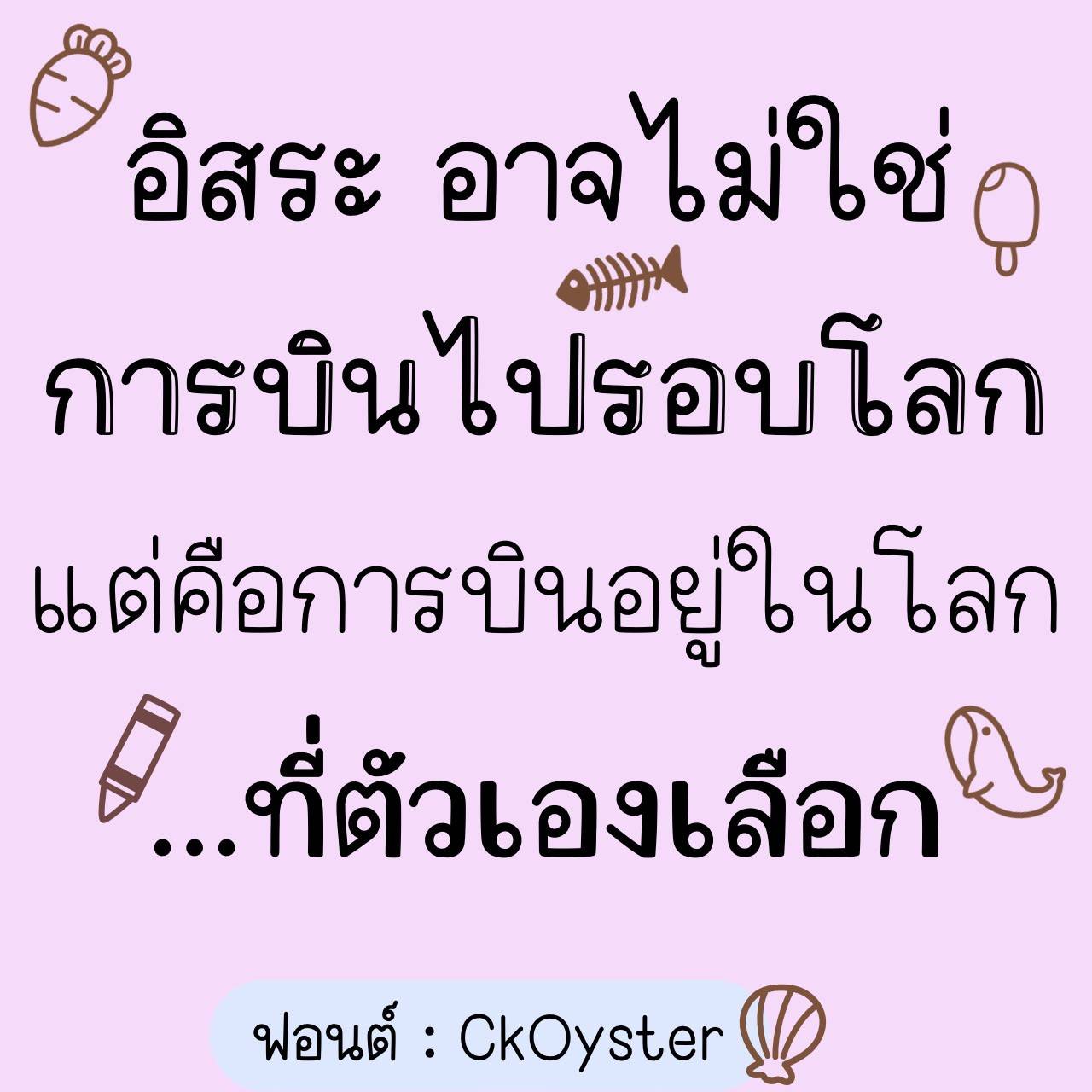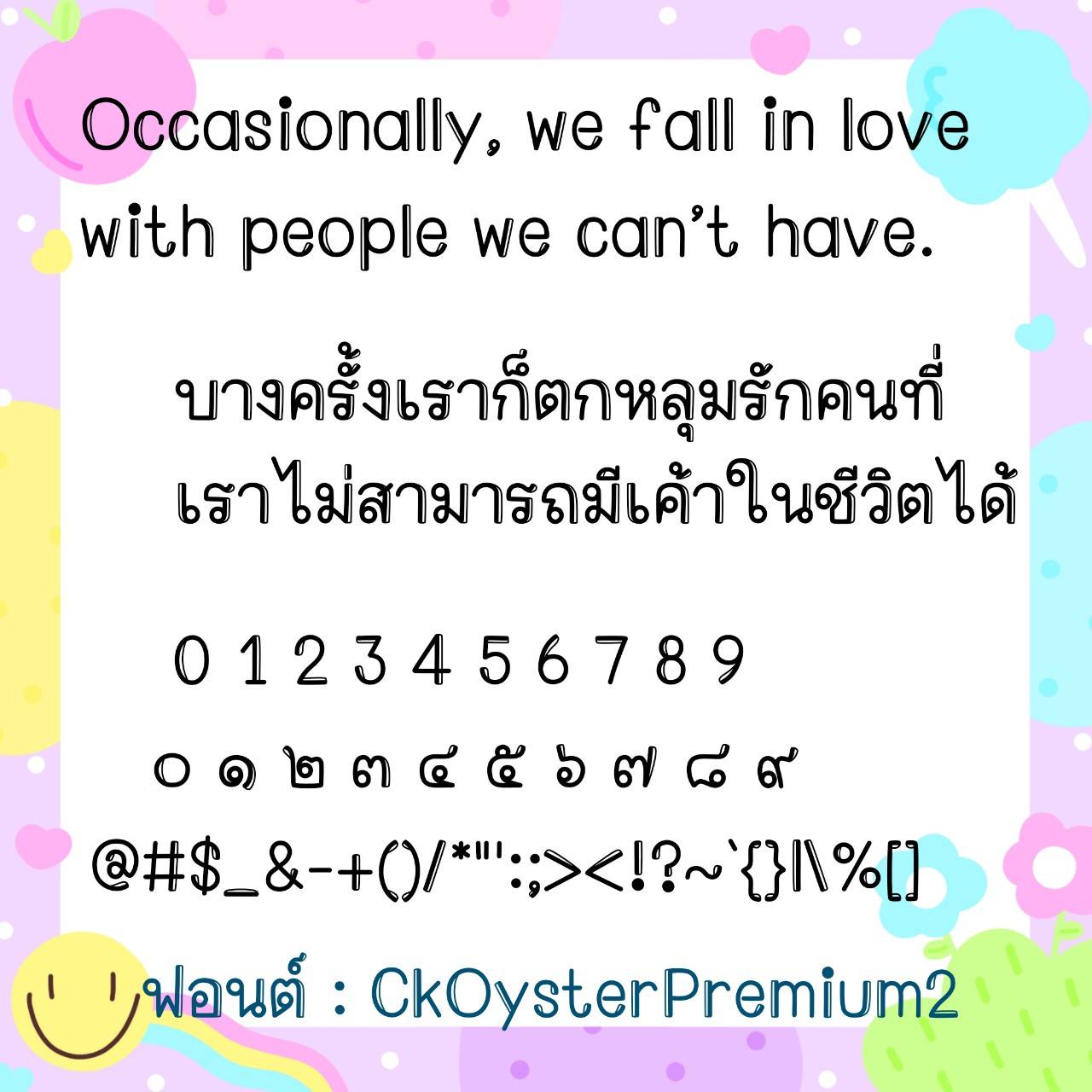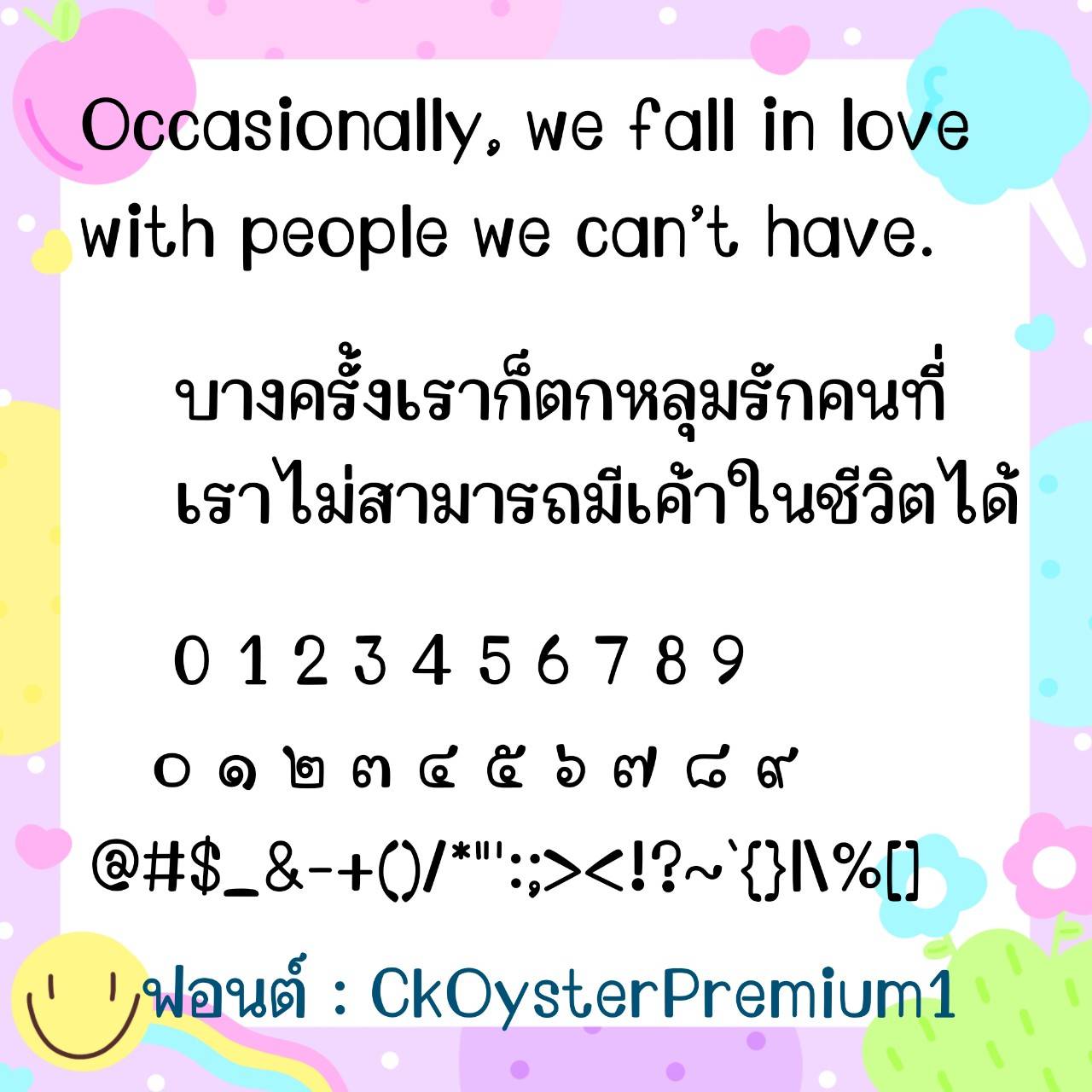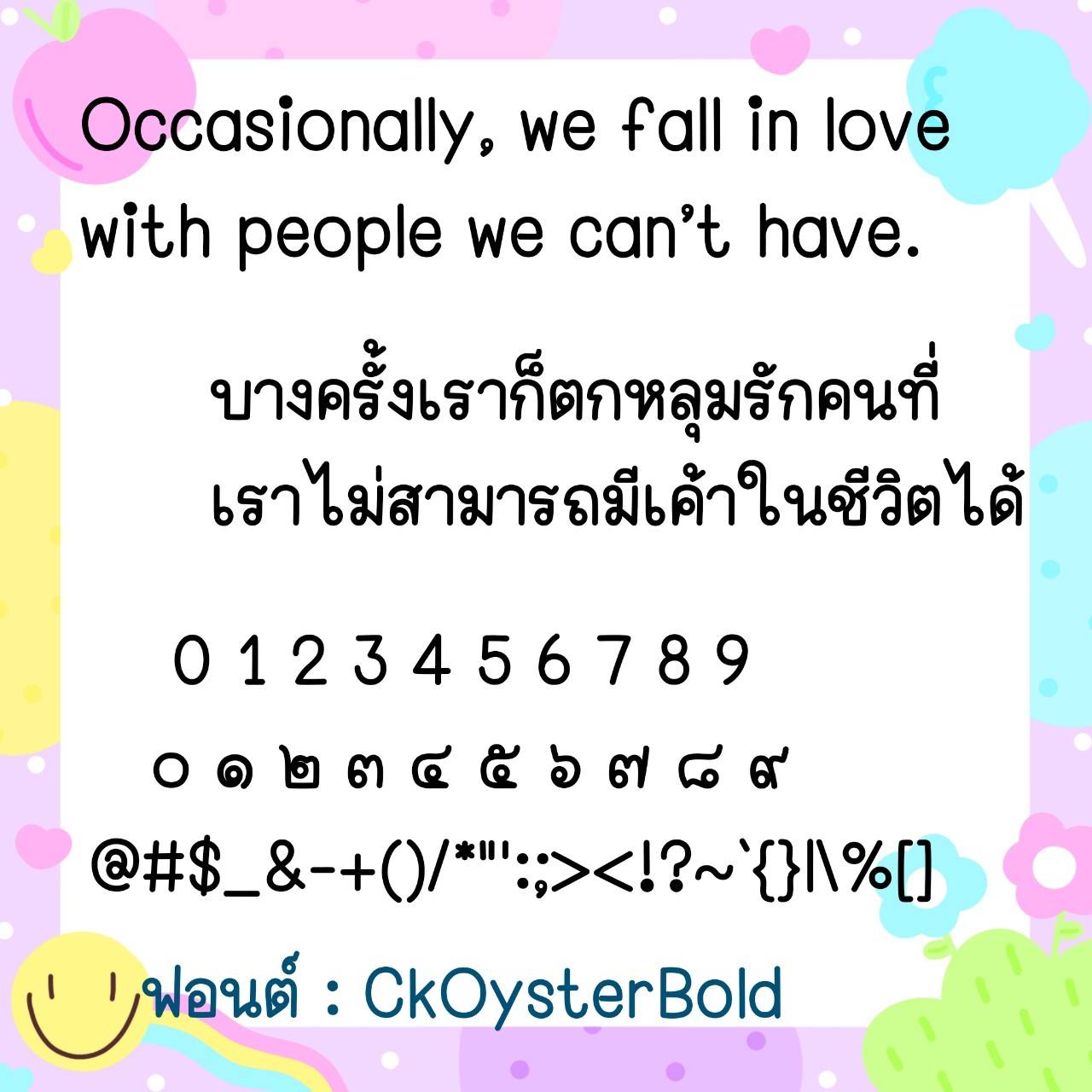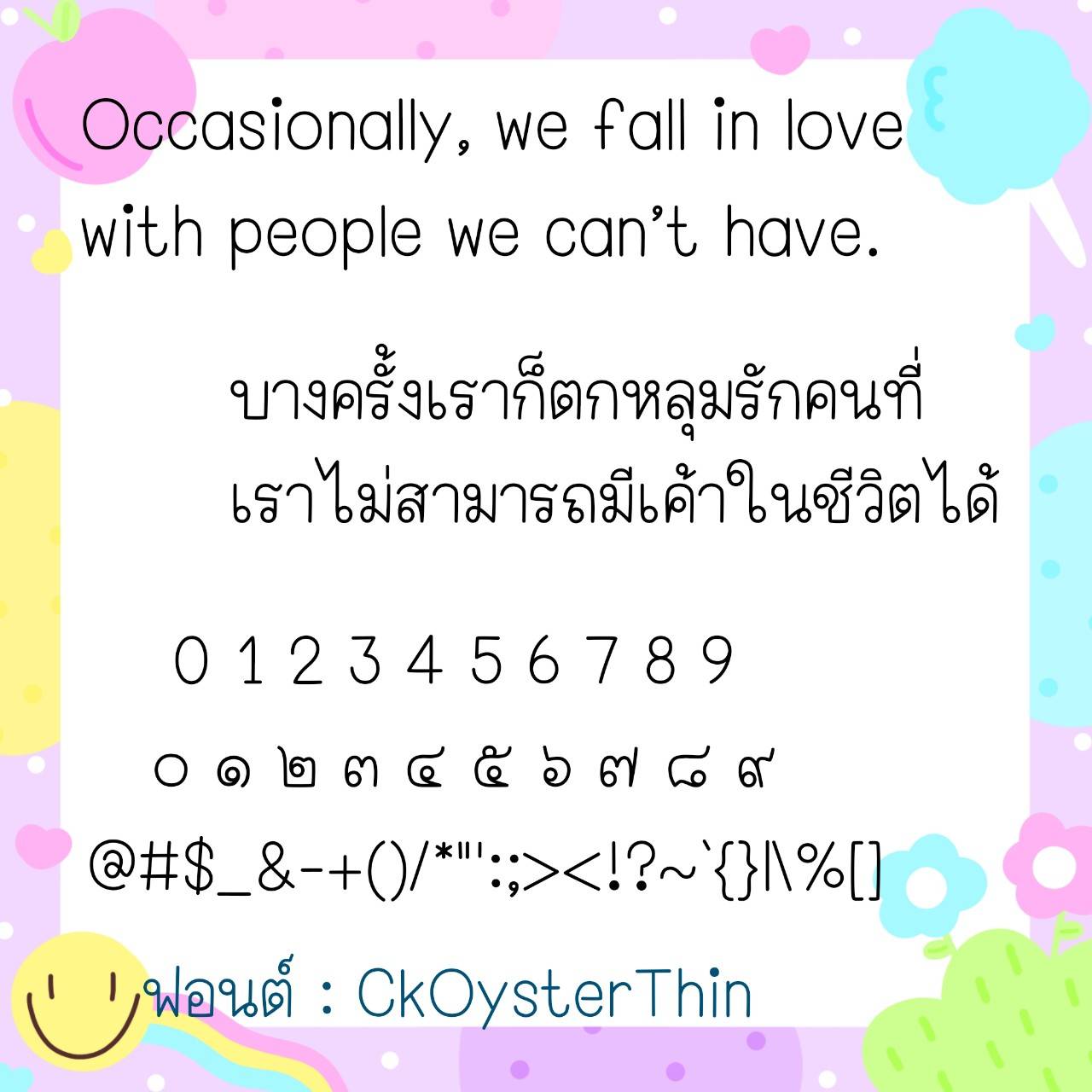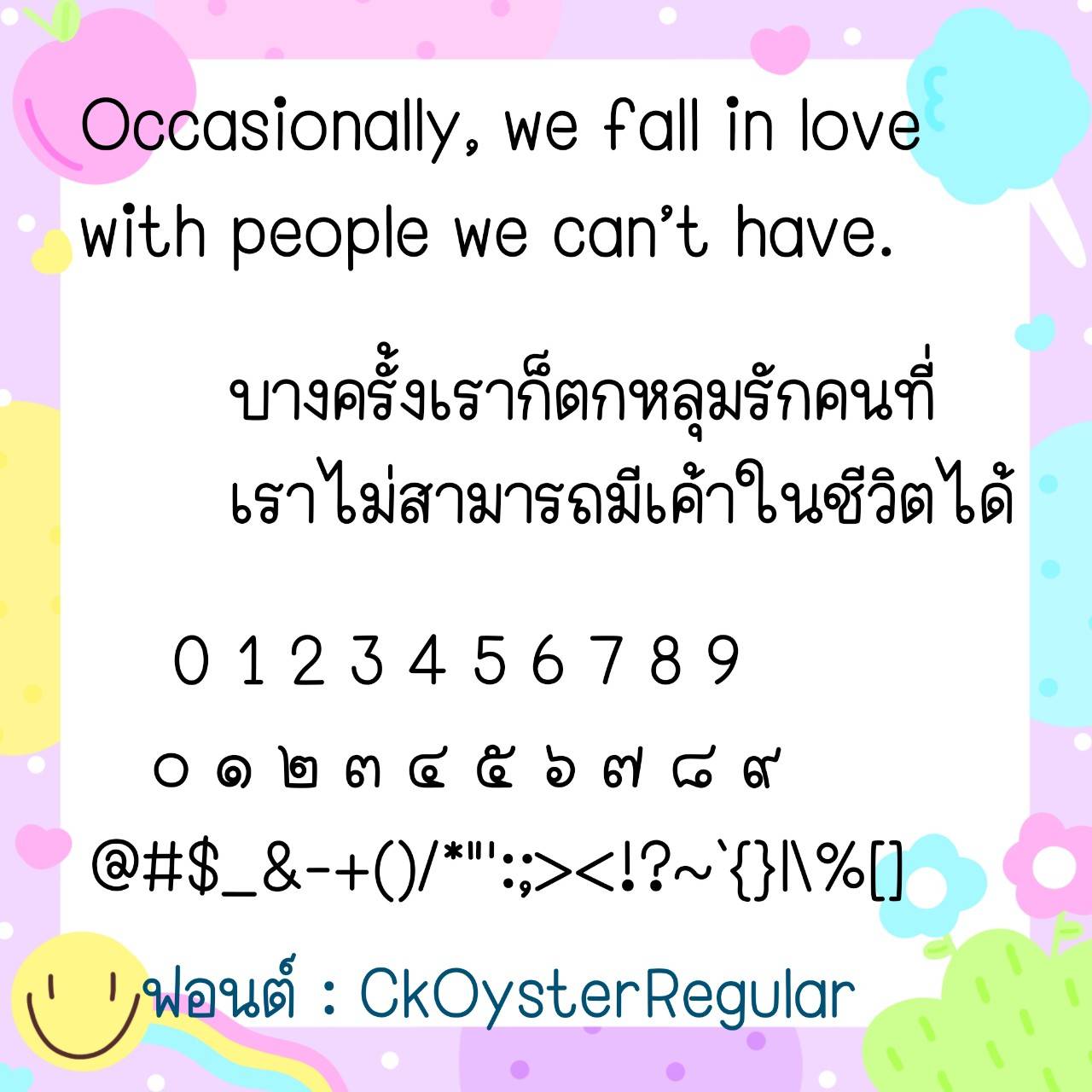
Font CkOyster
ชื่อสินค้า : Font CkOyster 💙
🔸 ฟอนต์ลายมือแนวเรียบร้อย ตัวนี้เน้นความเป็นระเบียบ แต่ยังดูมีความน่ารัก อ่านง่ายสบายตาเช่นเดิม ทั้งยังมีไฟล์พรีเมียมดูเรียบๆสวยๆ และมีไฟล์อิโมจิน่ารักๆ ที่ใช้แทนเลขไทยให้ด้วยค่ะ 🥰💙
🔹 This neat handwriting font emphasizes orderliness, but still looks cute and easy to read. It also has a premium file that looks simple and beautiful, and a cute emoji file that can be used instead of Thai numbers. 🥰💙